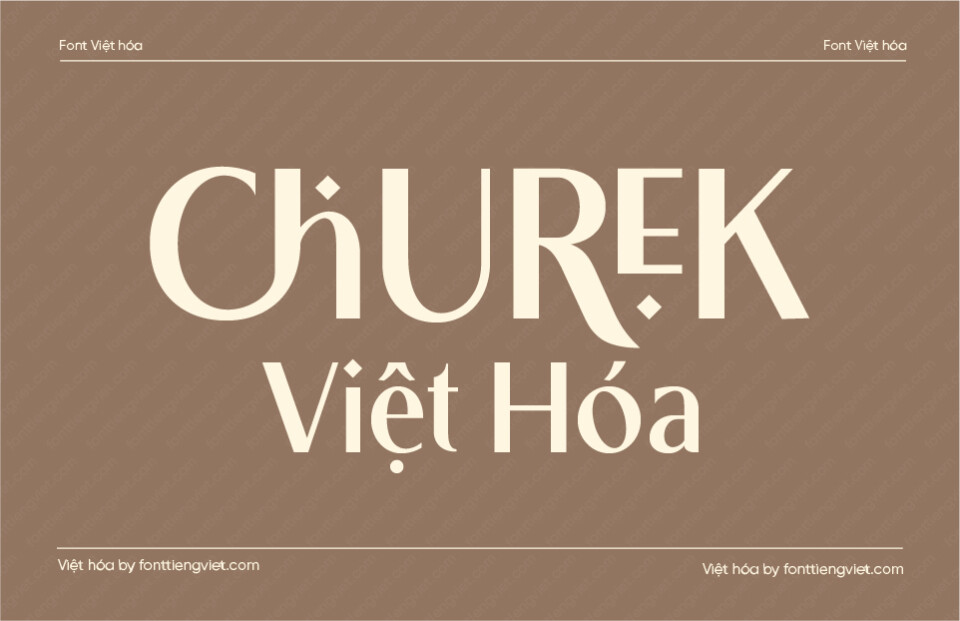
Font Việt hóa 1FTV VIP Churek: Bộ font chữ độc đáo dành cho thiết kế học đườngGiới thiệu về Font Việt hóa 1FTV VIP Churek trong học tập và sáng tạoTrong thế giới thiết kế đồ họa hiện đại, việc lựa chọn một Font Miễn Phí phù hợp không chỉ giúp truyền tải nội dung mà còn thể hiện phong cách riêng biệt của người sáng tạo. Font Việt hóa 1FTV VIP Churek nổi lên như một lựa chọn hàng đầu dành cho các bạn học sinh, sinh viên và thầy cô giáo khi muốn tạo ra những sản phẩm trình chiếu hay tài liệu học tập sinh động. Đây là một bộ phông chữ được tinh chỉnh kỹ lưỡng, hỗ trợ đầy đủ bộ gõ tiếng Việt, giúp loại bỏ hoàn toàn nỗi lo lỗi font khi soạn thảo các văn bản có dấu phức tạp.Những đặc điểm nổi bật của bộ Font Việt hóa 1FTV VIP ChurekPhong cách thiết kế hiện đại và trẻ trungFont Việt hóa 1FTV VIP Churek sở hữu những đường nét thanh thoát nhưng không kém phần mạnh mẽ, mang lại cảm giác năng động và mới mẻ. Cấu trúc của chữ cái được xây dựng dựa trên sự cân bằng giữa các nét thanh và nét đậm, tạo nên một tổng thể hài hòa và dễ nhìn trên nhiều loại màn hình khác nhau. Điều này cực kỳ quan trọng đối với các bài thuyết trình trên lớp, nơi mà học sinh cần sự rõ ràng để có thể theo dõi nội dung bài học từ xa một cách thuận tiện nhất.Khả năng ứng dụng đa dạng trong môi trường giáo dụcKhông chỉ dừng lại ở các bài giảng PowerPoint, Font Việt hóa 1FTV VIP Churek còn được ứng dụng rộng rãi trong việc thiết kế bìa báo tường, thiệp mời sự kiện trường học hay các poster cổ động. Với đặc tính dễ đọc, bộ font này giúp các thông điệp giáo dục trở nên gần gũi và thu hút hơn. Các bạn học sinh có thể sử dụng bộ phông này để trang trí cho các ghi chú cá nhân hoặc sổ tay học tập, giúp việc ghi nhớ kiến thức trở nên thú vị hơn bao giờ hết nhờ vào giao diện chữ viết đẹp mắt.Hướng dẫn sử dụng Font Việt hóa 1FTV VIP Churek hiệu quả nhấtKết hợp màu sắc và kích thước chữ phù hợpĐể Font Việt hóa 1FTV VIP Churek phát huy tối đa thẩm mỹ, người dùng nên chú ý đến việc phối màu. Khi sử dụng trên nền sáng, hãy chọn các tông màu đậm như xanh dương, đen hoặc đỏ đô để chữ nổi bật. Đối với các tiêu đề chính, bạn nên để kích thước chữ lớn và in đậm để tạo điểm nhấn mạnh mẽ. Ngược lại, trong các đoạn văn bản dài, hãy giữ kích thước vừa phải và khoảng cách dòng hợp lý để tránh gây mỏi mắt cho người đọc, đảm bảo tính khoa học cho tài liệu.Lưu ý về bản quyền và cài đặt fontKhi tải và cài đặt bộ font này, hãy đảm bảo bạn đã giải nén tệp tin đúng cách trước khi cài vào thư mục font của hệ thống. Việc sử dụng phiên bản Việt hóa giúp bạn tiết kiệm thời gian chỉnh sửa dấu câu thủ công. Hãy luôn kiểm tra lại văn bản sau khi áp dụng font để chắc chắn rằng các ký tự đặc biệt trong tiếng Việt không bị biến dạng, đảm bảo tính chuyên nghiệp tuyệt đối cho sản phẩm thiết kế của mình trong mắt thầy cô và bạn bè đồng trang lứa.Kết luận về giá trị của Font Việt hóa 1FTV VIP ChurekViệc sở hữu Font Việt hóa 1FTV VIP Churek trong bộ sưu tập công cụ thiết kế sẽ giúp các bạn học sinh tự tin hơn trong các dự án sáng tạo tại trường. Bộ font này không chỉ là một công cụ trình bày đơn thuần mà còn là nguồn cảm hứng để phát triển tư duy thẩm mỹ. Nếu bạn đang tìm kiếm những tài nguyên chất lượng, hãy tham khảo ngay tại Font Miễn Phí, Font Việt Hóa, Font Việt hóa 1FTV VIP Churek để cập nhật thêm nhiều lựa chọn tuyệt vời khác. Sự kết hợp giữa kiến thức và hình thức trình bày chuyên nghiệp chính là chìa khóa dẫn đến thành công trong học tập.
Font Việt hóa 1FTV VIP Churek